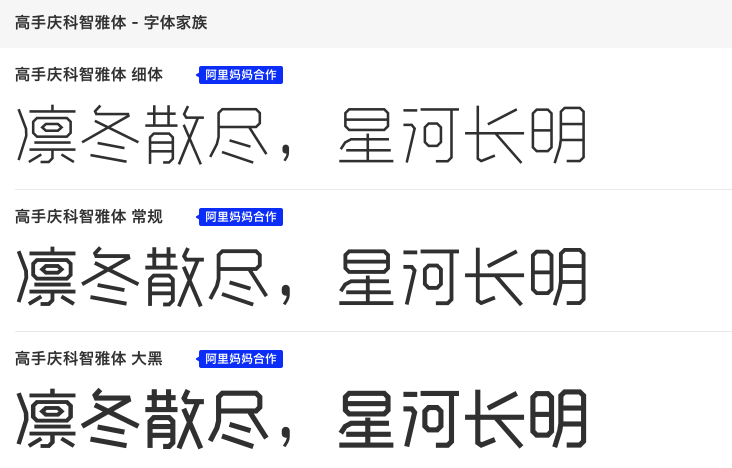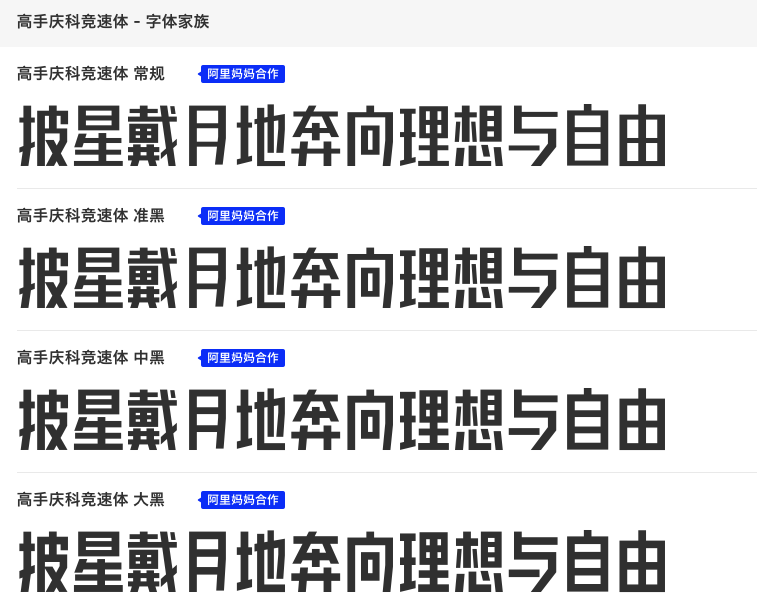
设计必备:高手庆科字体家族推荐
在设计领域,字体的选择往往决定了作品的整体风格与氛围。今天,为大家推荐两款来自高手庆科系列的字体家族,它们各具特色,非常适合用于各种设计场合。
首先,让我们来看看“高手庆科竞速体”字体家族。这款字体字型瘦长工整,布白均匀,中宫紧凑,重心平稳。其直线设计使得横竖笔画视觉等粗,而“钩”笔画则采用去钩后笔画末端往内部加斜的处理方式,使得整体更加简洁工整。该字体家族包含4个字重,从细到粗平滑过渡,无论是标题还是正文,都能展现出良好的视觉表现与阅读体验。
接下来,我们来看看“高手庆科智雅体”字体家族。这款字体同样以直线为主,但中宫略大,布白均匀,重心统一。笔画设计简洁无过多装饰,横竖笔画视觉等粗,同时以连笔折笔为特色,使得整体视觉统一且多变灵活。该字体家族共包含3个字重,从细体到粗体平滑过渡,同样适用于多种风格与样式的排版。
两款字体家族都注重细节处理,无论是内部留白还是笔画起收笔处的平切处理,都展现出高手庆科对字体设计的精湛技艺。它们不仅具有良好的视觉表现与阅读体验,还能适配多种风格与样式的排版,是设计师们不可或缺的选择。